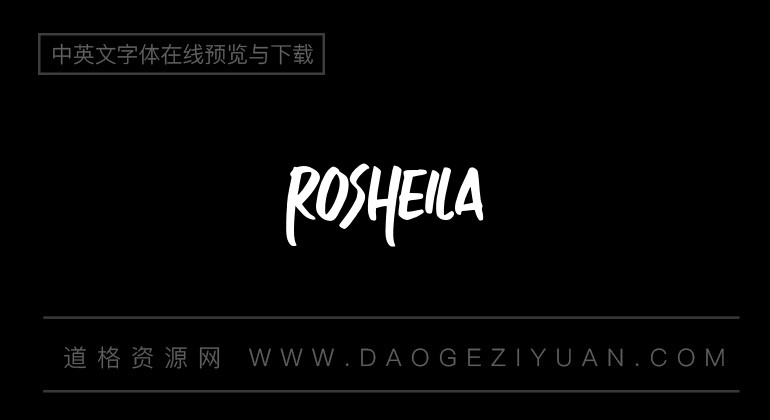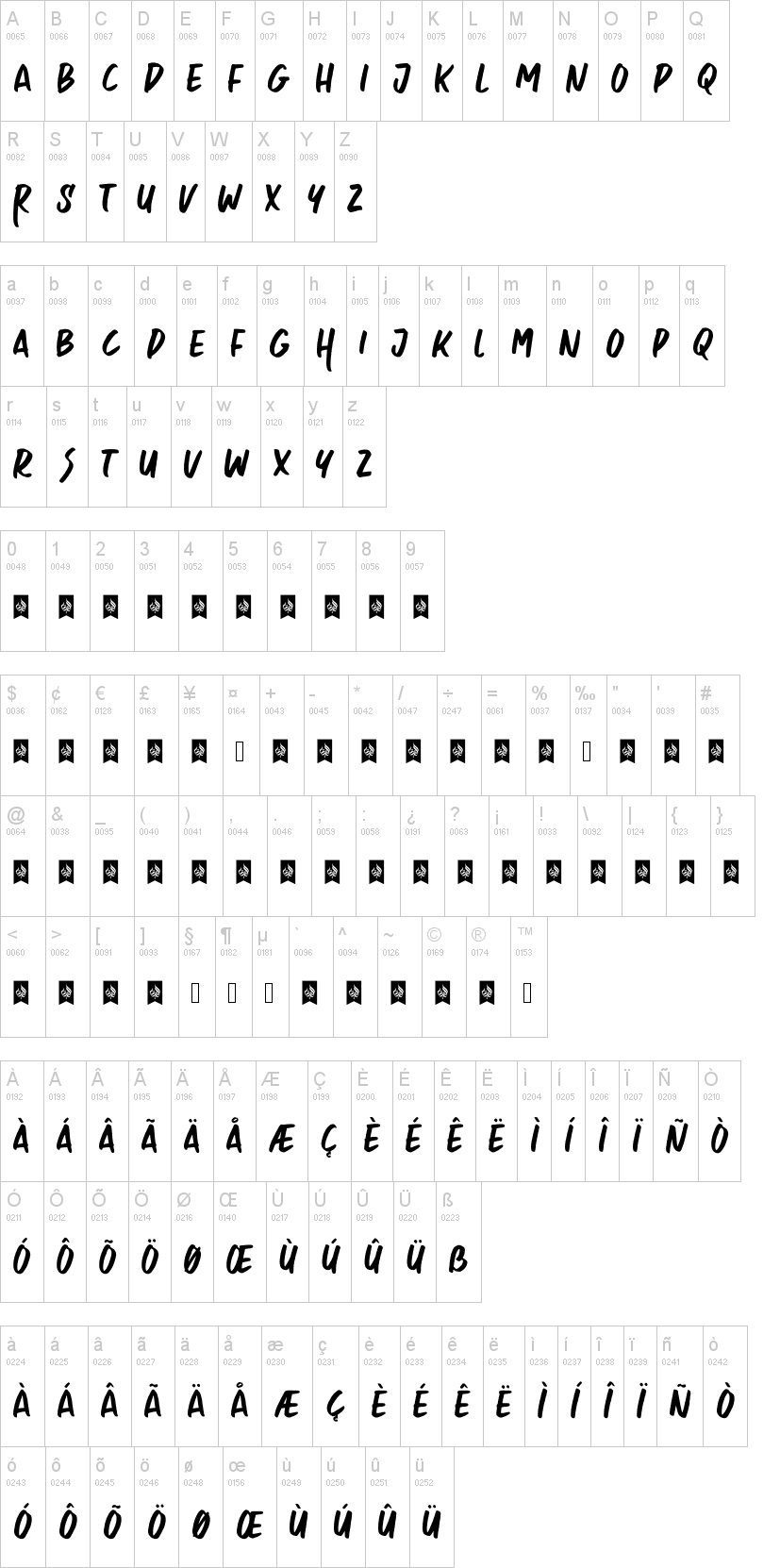
Rosheila 字体是一种优雅和时尚的手写字体,适用于多种设计风格。它具有优美的连笔和流畅的线条,展现出一种自然而舒适的感觉。该字体由 Nissa Nurfajriyani 设计,包含有大写和小写字母、数字、标点符号和多种特殊字符。Rosheila 字体非常适合用于个人品牌、印刷品、海报、包装、徽标设计等多种场合。内容介绍
Rosheila是一款非常不错的手写艺术字体,具有很好的视觉感,适合于文化类的宣传设计、商业类品牌的广告和产品包装设计以及个性化文字排版等较多场景。